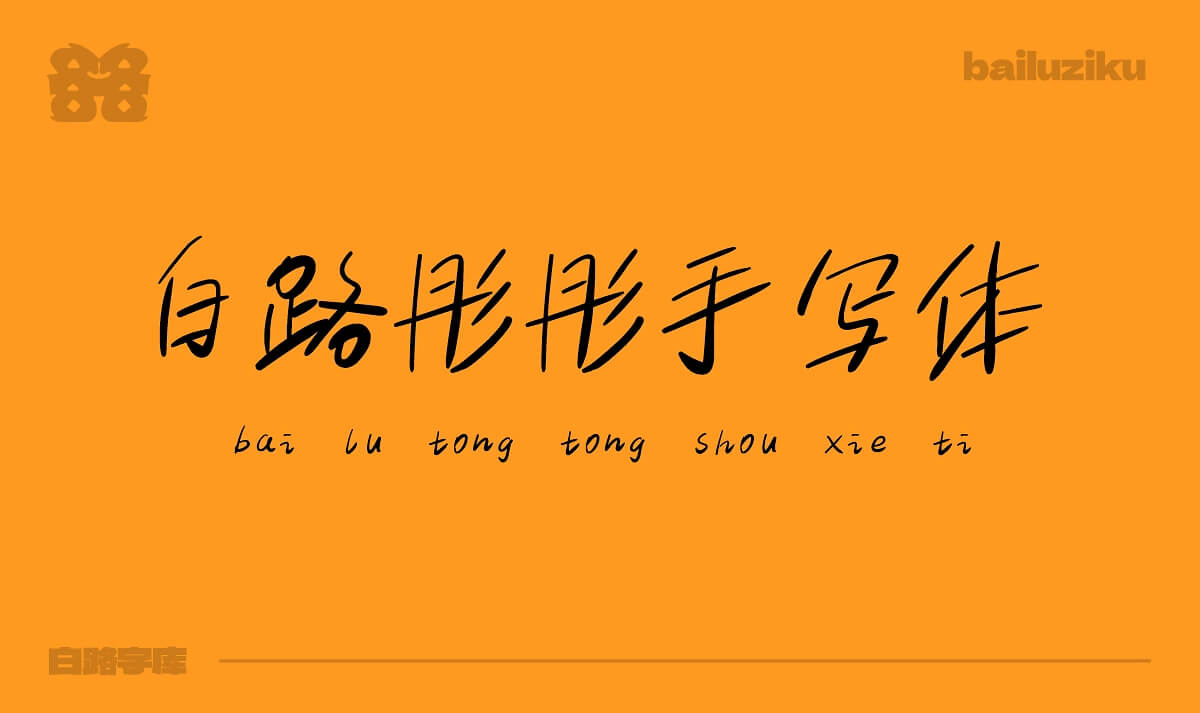
白路彤彤手写体
自己手写一款字体,字符加数字,英文及标点符号共6796个字符,该字库风格为手写偏文艺,喜欢的可以下载使用。 已注册版权,附件有字体文件。
白路彤彤手写体是山人白路自己手写一款字体,字符加数字,英文及标点符号共6796个字符,该字库风格为手写偏文艺,现在已正式开放免费商用,喜欢的可以下载使用。可以的话给作者打个赏,请白路兄喝杯奶茶吧!